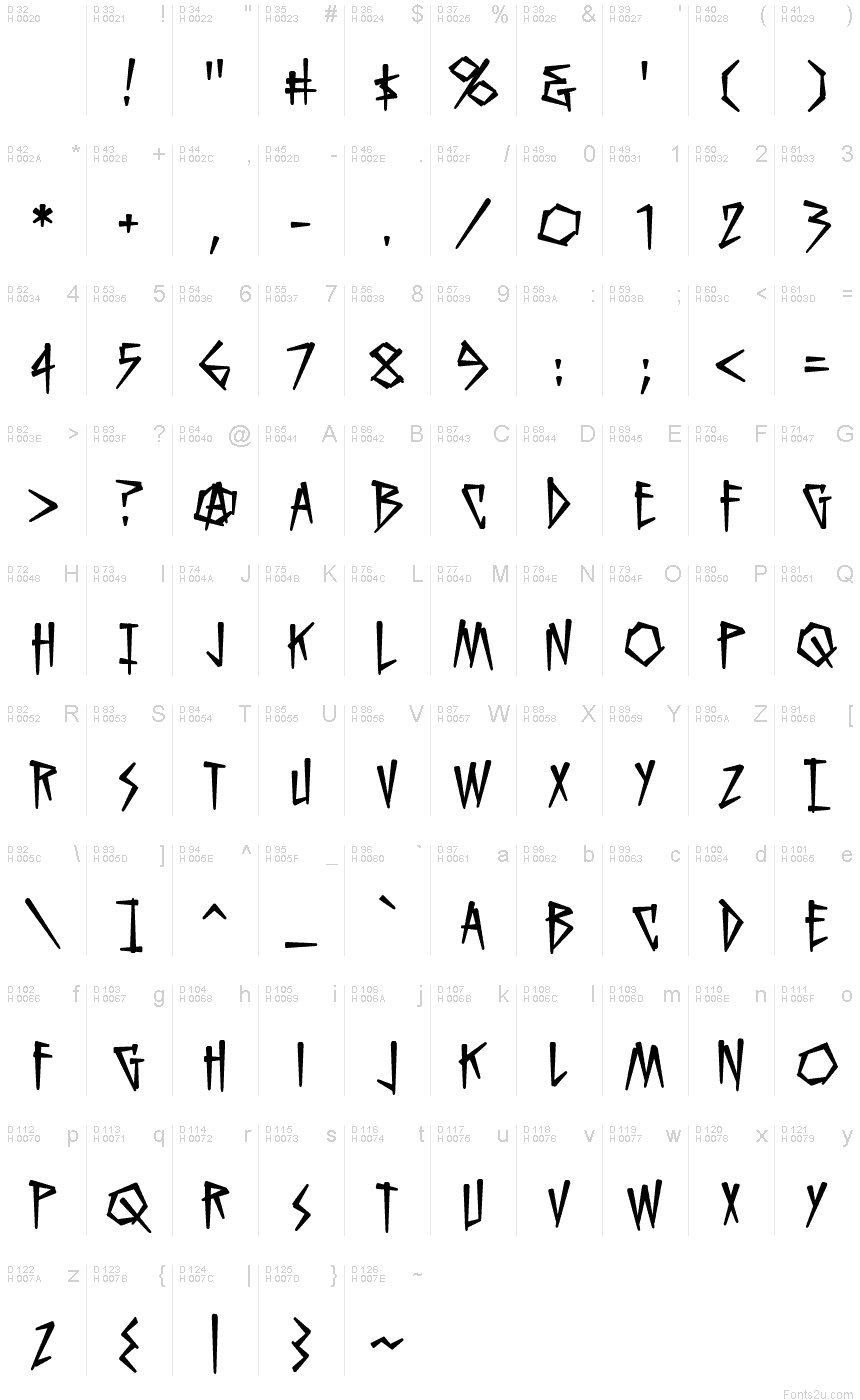
KillCrazy BB フォント
KillCrazy BB
Nate Piekos
Kill Crazy(Nate Piekos作)は、急いで切り出したような文字が特徴の、ホラー系無料ディスプレイフォントです。太くギザギザで不均一なストロークと鋭い先端が、手書きのような緊張感を生み出し、洗練されたスタジオデザインとは一線を画す、コミックのような叫びを表現しています。
この無料フォントは、ポスターのタイトルやハロウィンのフライヤー、パンクジン、コミックの効果音、ホラーテイストのパッケージデザインに最適です。ここでは、きれいな幾何学模様よりも、この荒削りな質感が雄弁に語ります。また、ゴア描写や安っぽい小道具に頼ることなく、ワイルドで引っ掻いたようなトーンが必要な、短いカバーライン、タイトルカード、ロゴタイプにも適しています。